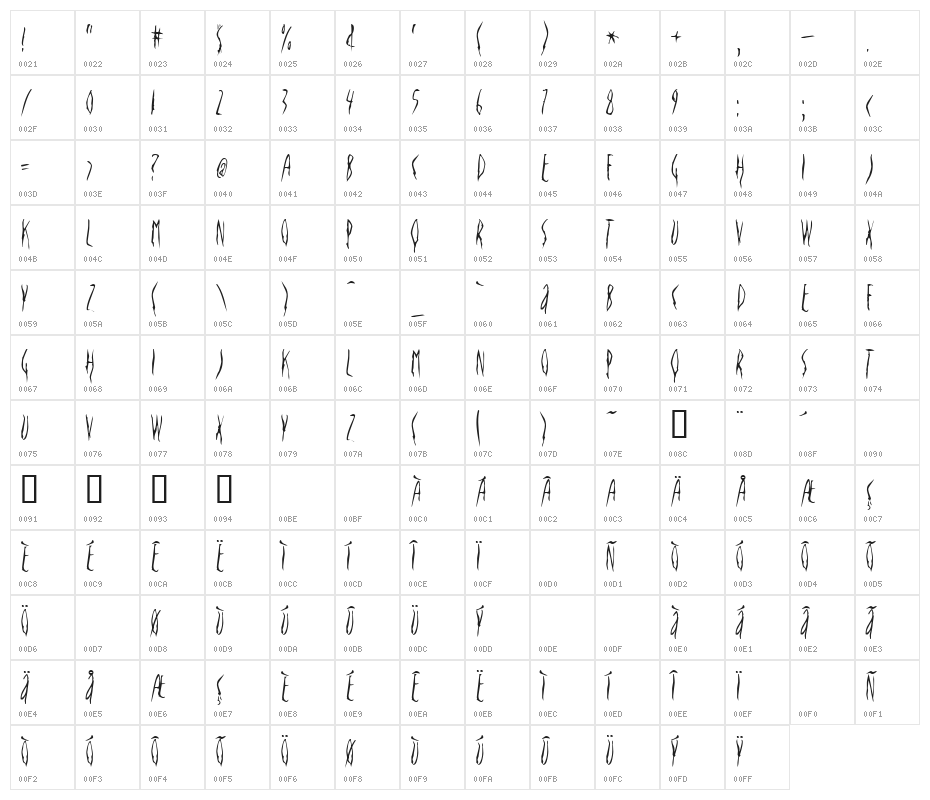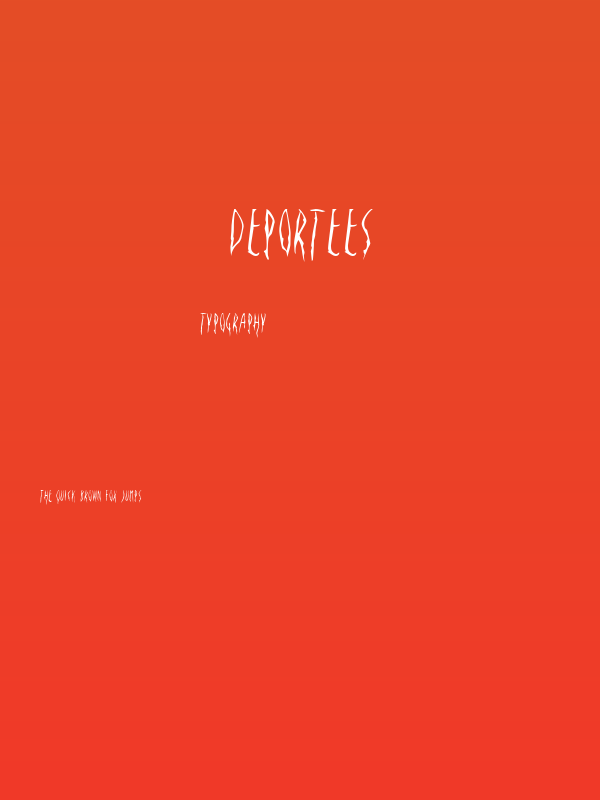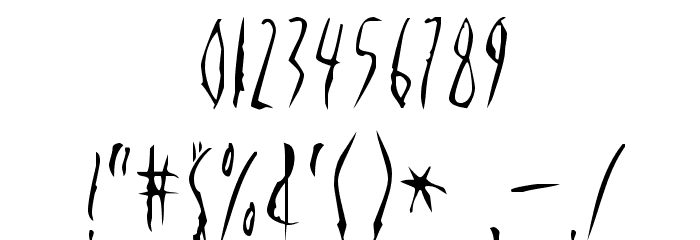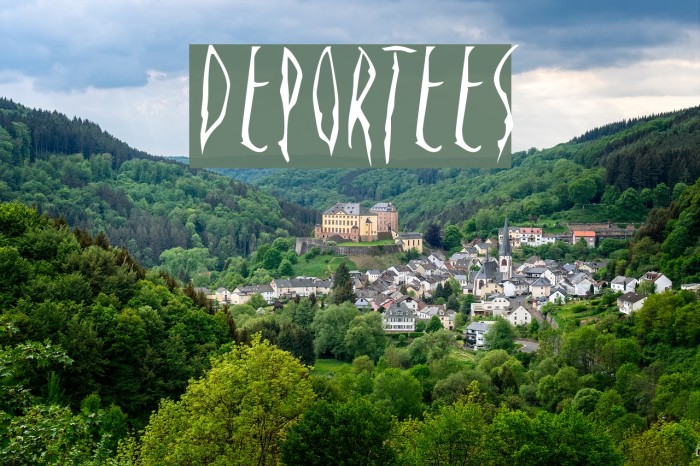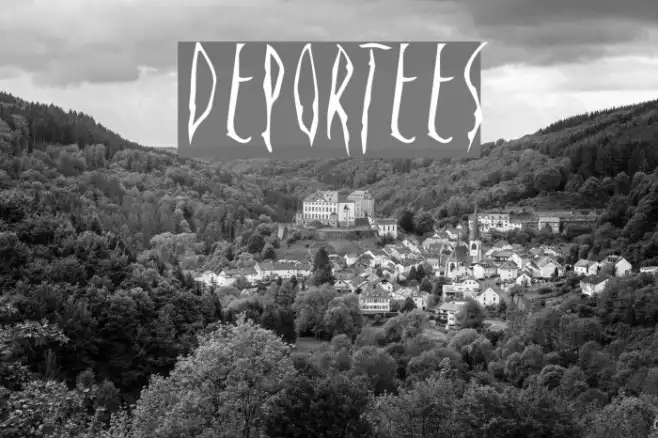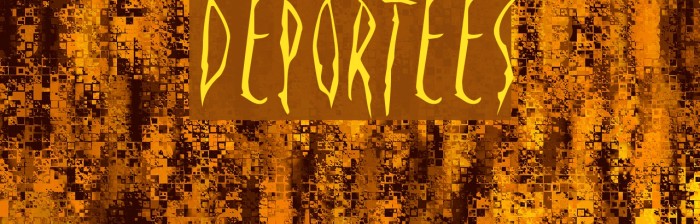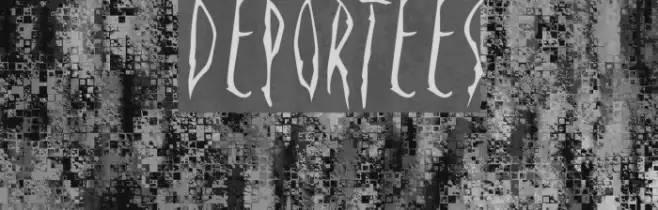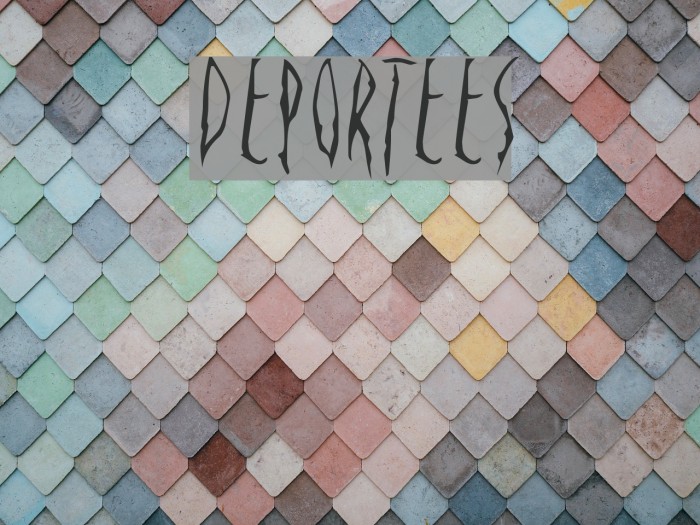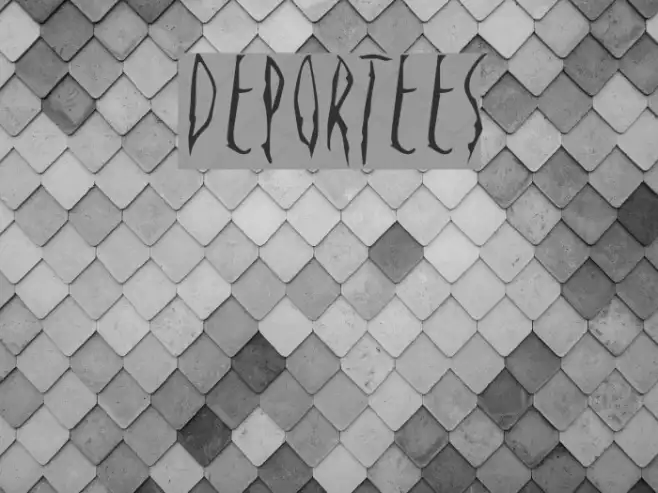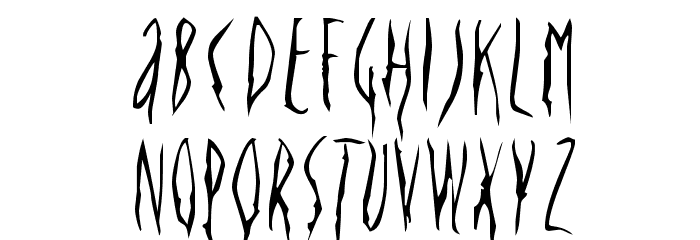
Deportees Font
| Vorgeschlagene Projekte | Ideal for horror-themed posters, edgy album covers, or any project needing a dramatic and bold typeface. |